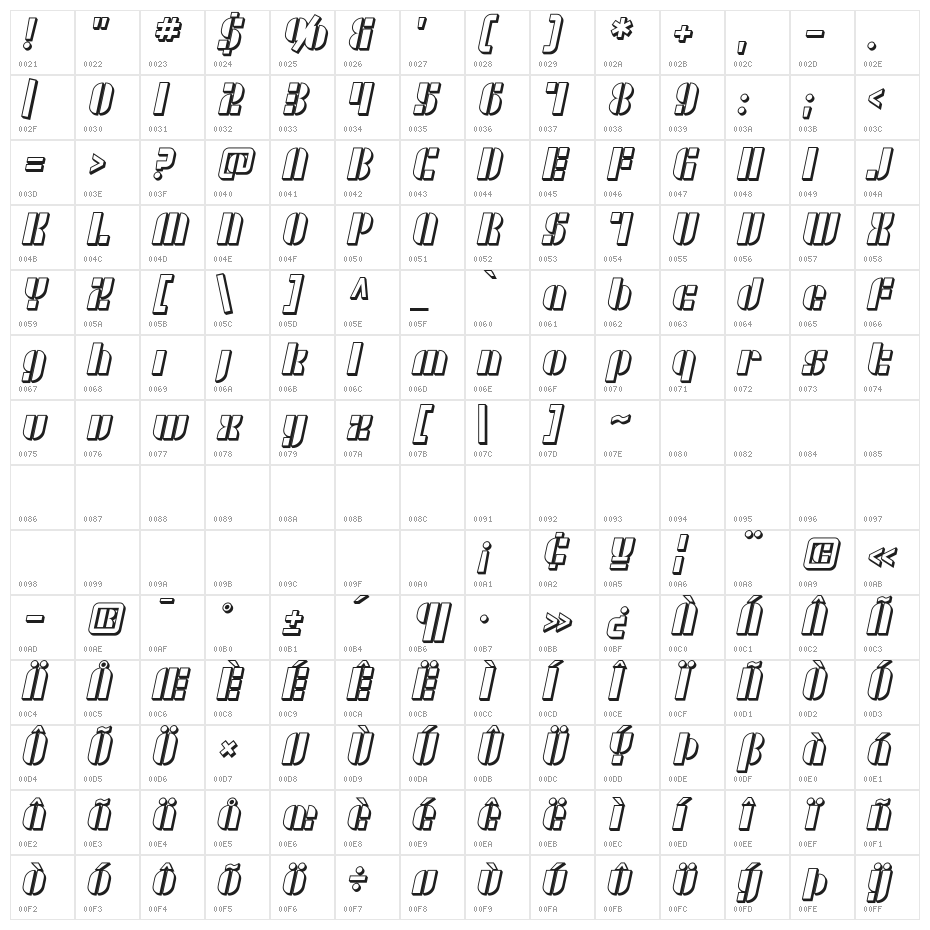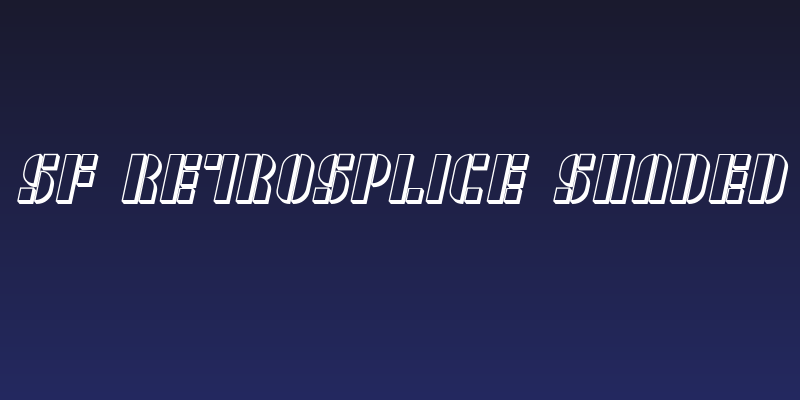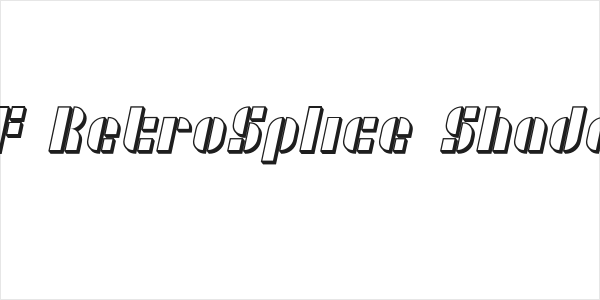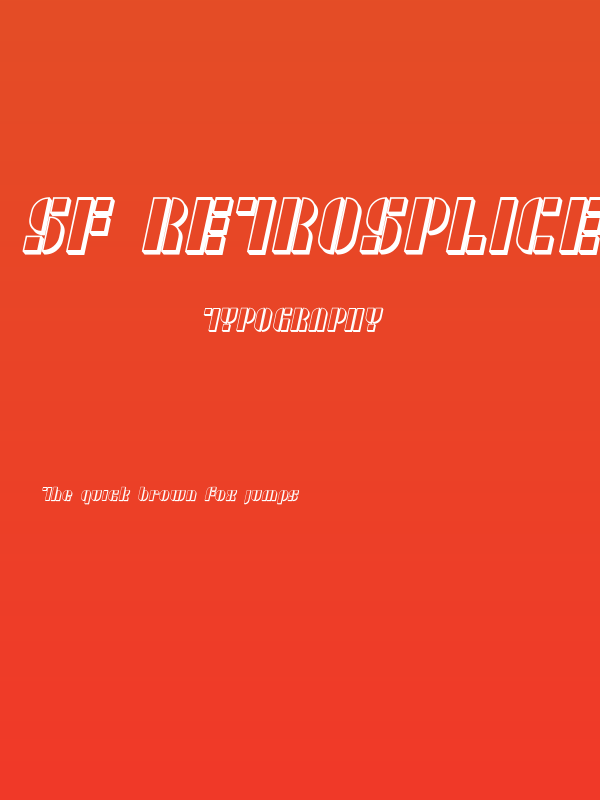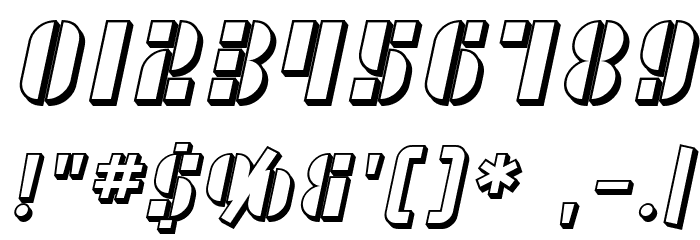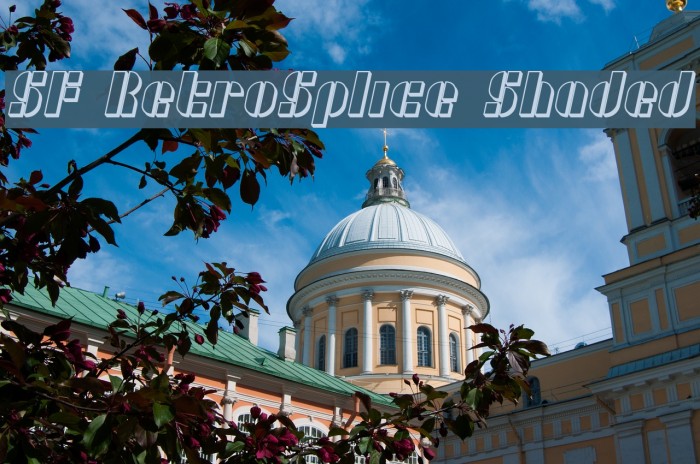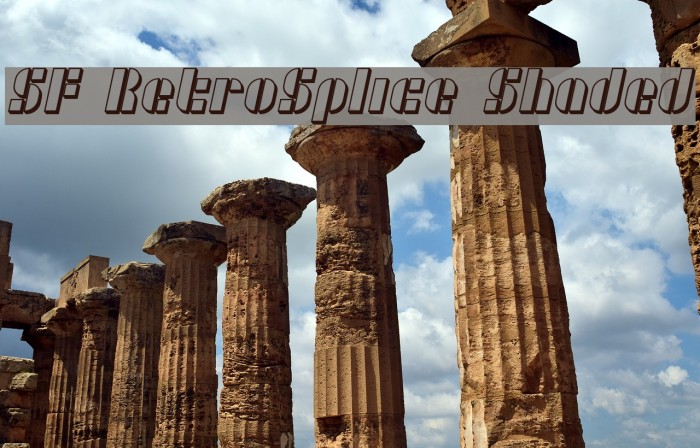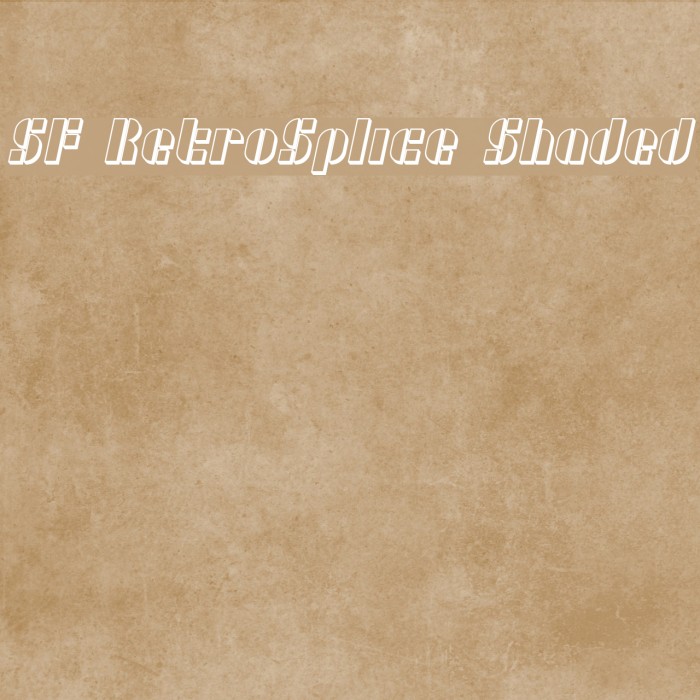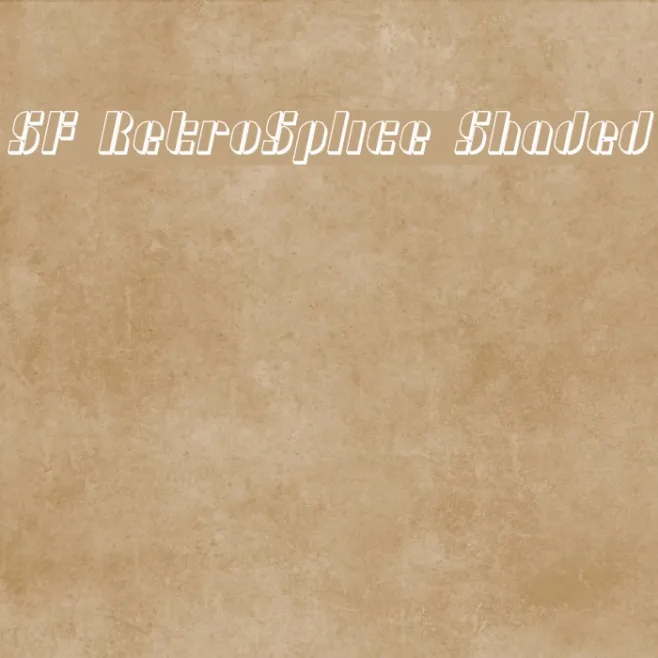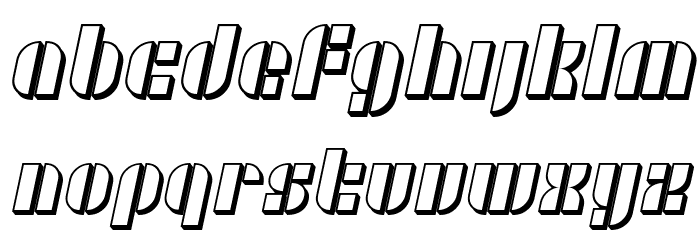
SF RetroSplice Shaded Font
| Style général | Retro |
| Projets proposés | Ideal for vintage-themed posters, retro branding, and eye-catching headlines. |